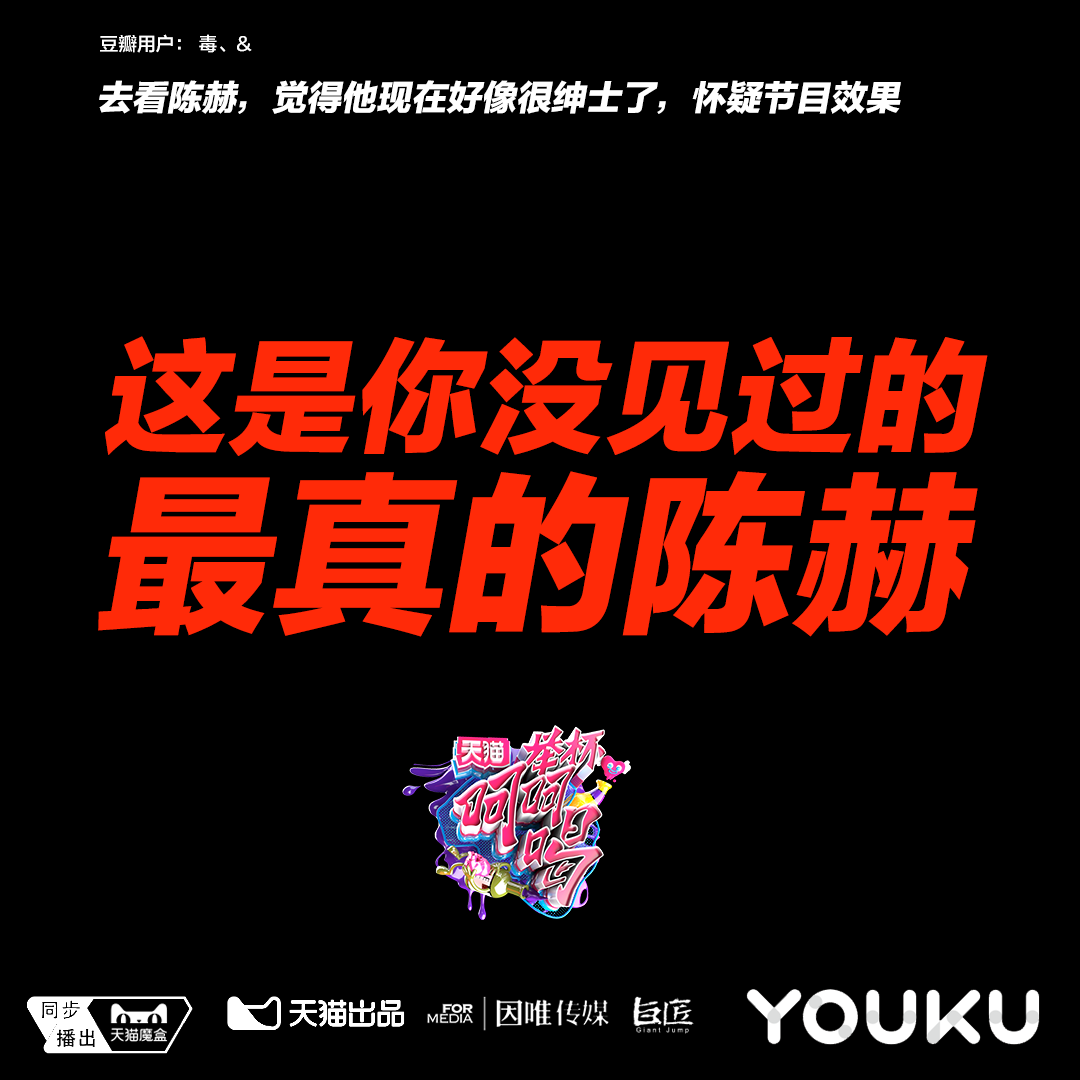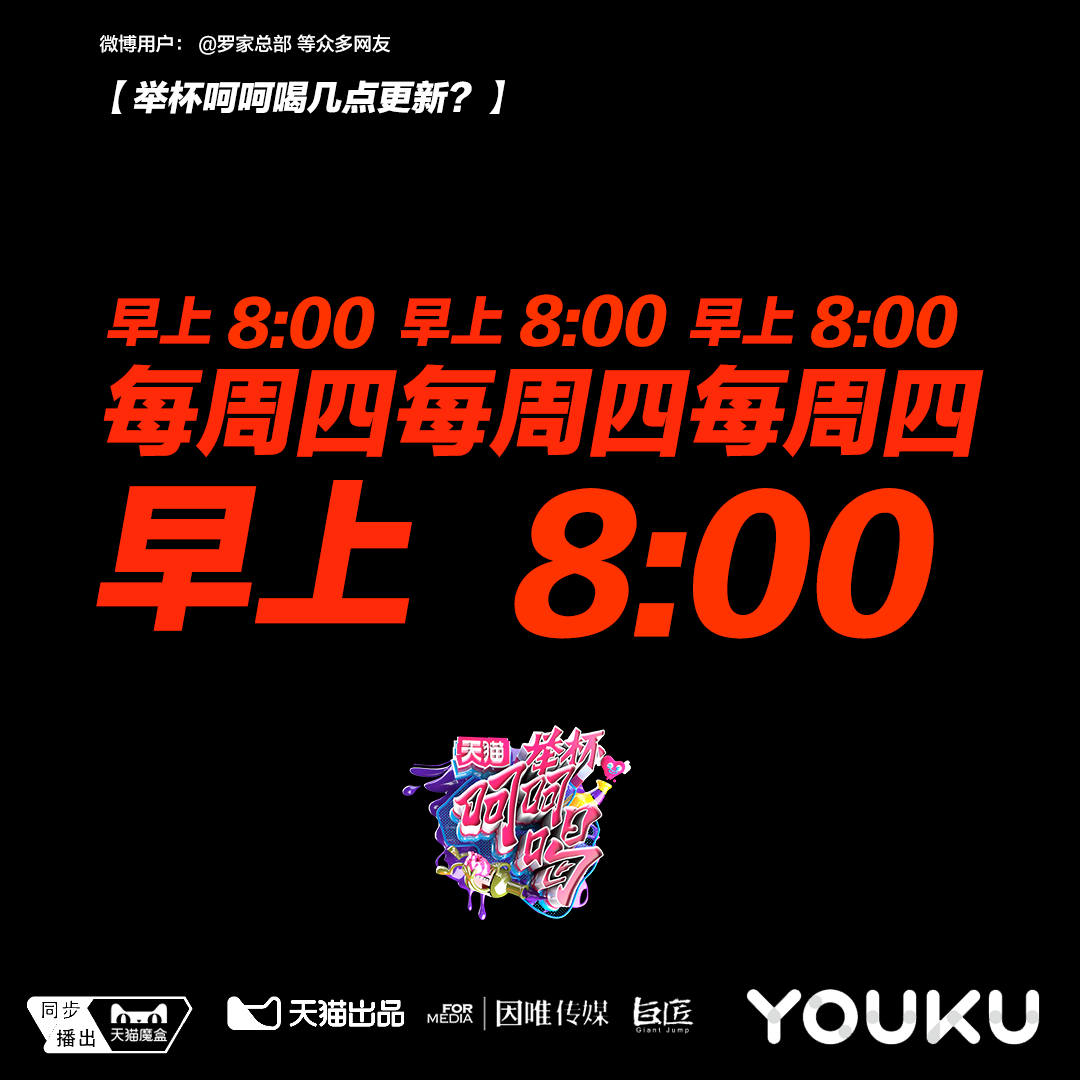
方正兰亭黑家族
方正兰亭黑家族 2009亚洲最具影响力设计铜奖
齐立
黑体
2006
方正兰亭黑是国内最早专门为屏幕阅读设计、并由此衍生出的家族家族字体。兰亭黑字面大,字型朴素清秀,结构严谨,黑白均匀,重心一致;笔划制作精良,线条刚柔相济,简洁有力。阅读舒适流畅,有着鲜明的时代感。
2004年方正公司授权微软公司在Vista以后的Windows操作系统中使用方正兰亭黑和方正兰亭粗黑。在微软系统中,该字体被称为“微软雅黑”。
兰亭黑家族字体先后被美国高通公司的手机芯片、三星手机、华为手机、小米手机、苹果Mac OS Mountain Lion系统等产品使用。
获奖情况:2009亚洲最具影响力设计铜奖
2009年,方正兰亭黑荣获“2009亚洲最具影响力设计铜奖"
方正兰亭黑系列在苹果Mac OS系统的应用
在三星手机中的应用
在多看阅读软件中的应用
在Kindle阅读器中的应用
小米手机MIUI 8使用了基于方正兰亭黑定制的“小米兰亭”作为系统字体
小米发布的MIUI 11动态字体系统中,应用了依靠最新可变字体技术升级的小米兰亭Pro VF
作为一款为屏幕阅读而生的现代黑体,方正兰亭黑除了在屏显方面表现出色,
也得到了国内众多精品杂志、图书的垂青,广告设计师、包装设计师们也对它钟爱有加……
它的魅力已渗透到了人们生活的方方面面,成为新世纪黑体中当之无愧的“扛鼎之作”。
书籍内页及封面装帧设计
产品宣传
产品海报
软件UI
活动海报